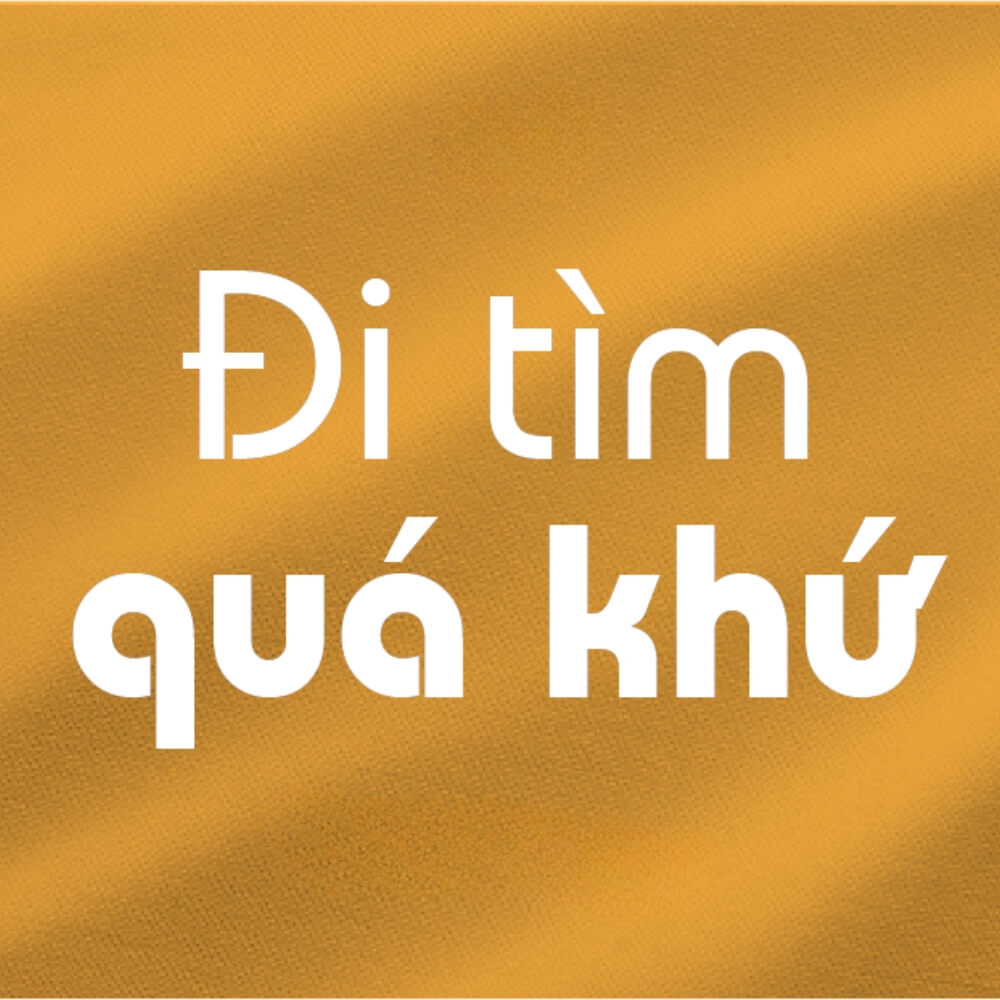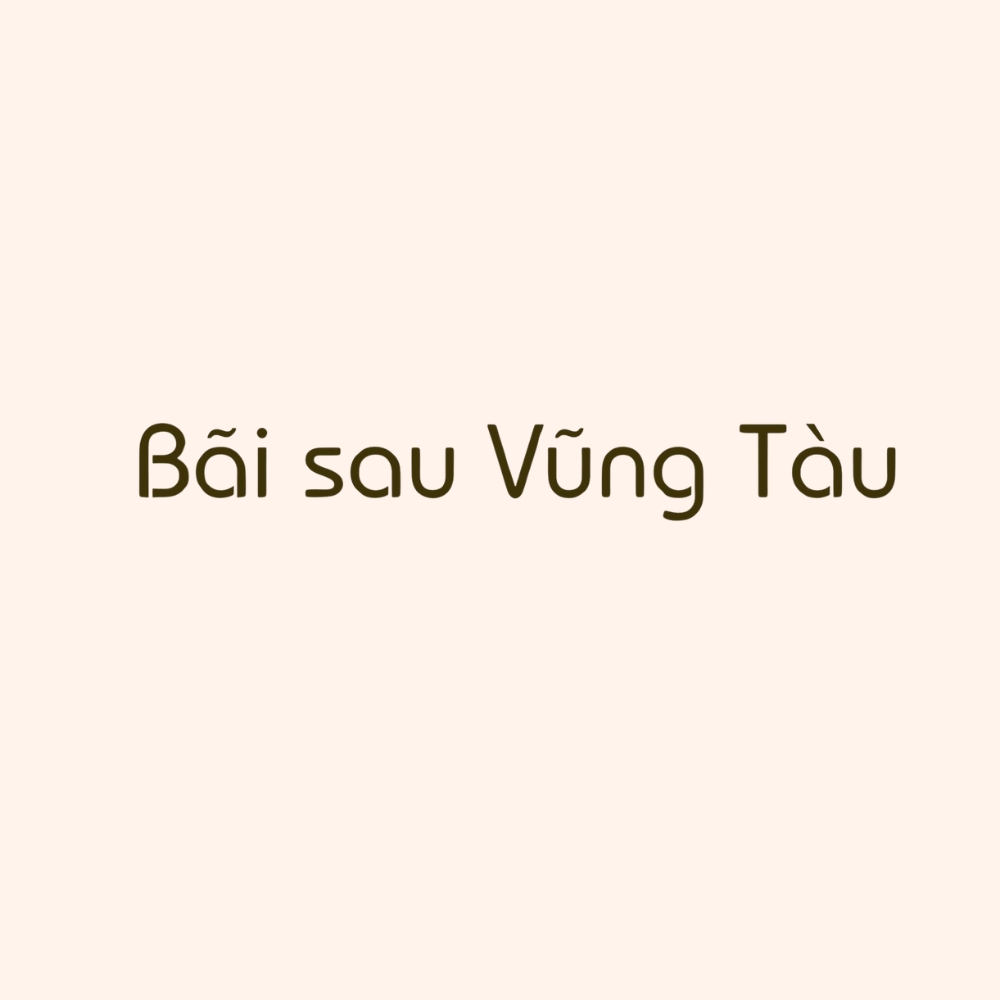
Nhiều designer khi tìm font việt hóa UVN Bai Sau thường gặp tình trạng tải về nhưng chữ hiển thị sai dấu hoặc thiếu ký tự tiếng Việt. Một số file được chia sẻ trên internet chỉ là phiên bản chưa việt hóa hoàn chỉnh nên khi dùng trong poster hoặc thiết kế logo rất dễ phát sinh lỗi. Khi font không chuẩn, bố cục chữ sẽ bị lệch và làm giảm chất lượng thiết kế.
| Tên font | UVN Bãi Sau |
| Kiểu chữ | Sans-serif hiện đại |
| Hỗ trợ | Tiếng Việt đầy đủ |
| Ứng dụng | Logo, poster, banner, tiêu đề |
Bộ font chữ hiện đại uvn bai sau việt hóa thường được sử dụng trong các thiết kế mang phong cách tối giản và hiện đại.
Đặc điểm nổi bật của font việt hóa UVN Bai Sau
Trong nhóm font sans-serif hiện đại, font việt hóa UVN Bai Sau được nhiều designer lựa chọn nhờ cấu trúc chữ gọn gàng và dễ đọc. Font này mang phong cách đơn giản nhưng vẫn đủ cá tính để tạo điểm nhấn trong thiết kế.
Những đặc điểm nổi bật của font này gồm:
- Nét chữ rõ ràng và gọn gàng.
- Phong cách thiết kế hiện đại.
- Dễ đọc ở nhiều kích thước khác nhau.
- Phù hợp với các thiết kế tối giản.
Nhờ những đặc điểm này, download font UVN Bai Sau việt hóa thường được sử dụng trong các dự án thiết kế thương hiệu hoặc truyền thông.
Ứng dụng font việt hoá UVN Bai Sau trong thiết kế
Nhờ kiểu chữ hiện đại và dễ đọc, font việt hóa UVN Bai Sau có thể sử dụng trong nhiều loại thiết kế khác nhau. Font này đặc biệt phù hợp với các dự án cần sự đơn giản nhưng vẫn chuyên nghiệp.
Một số ứng dụng phổ biến của font gồm:
- Thiết kế logo: tạo cảm giác hiện đại và chuyên nghiệp.
- Poster quảng cáo: tiêu đề dễ đọc và rõ ràng.
- Banner truyền thông: phù hợp cho các chiến dịch marketing.
- Thiết kế website: font sans-serif giúp nội dung dễ đọc hơn.
Khi kết hợp với các font serif hoặc script, font uvn bai sang nang viet hoa có thể tạo ra bố cục thiết kế hài hòa và cân đối.
03 lưu ý khi sử dụng font UVN Bai Sau trong thiết kế
Mặc dù font việt hóa UVN Bai Sau khá dễ sử dụng, nhưng designer vẫn nên lưu ý một số điểm để đảm bảo thiết kế đạt hiệu quả tốt nhất.
- Chọn kích thước chữ hợp lý: giúp tiêu đề nổi bật nhưng không quá lớn.
- Kết hợp với font khác: pairing với script hoặc serif giúp bố cục phong phú hơn.
Những lưu ý này sẽ giúp bạn sử dụng font chữ hiện đại UVN Bai Sau việt hóa hiệu quả hơn trong các dự án thiết kế.
Font UVN Bai Sau phù hợp thiết kế gì?
Font này phù hợp cho logo, poster và banner nhờ phong cách chữ hiện đại và dễ đọc.
Font UVN Bai Sau có hỗ trợ tiếng Việt không?
Phiên bản việt hóa hỗ trợ đầy đủ dấu tiếng Việt nên có thể dùng cho thiết kế tại Việt Nam.
Font việt hóa UVN Bai Sau là lựa chọn phù hợp cho những thiết kế mang phong cách hiện đại và tối giản. Khi sử dụng đúng phiên bản download font uvn bai sau việt hóa, designer đảm bảo chữ hiển thị đầy đủ dấu tiếng Việt và giữ được độ chính xác của thiết kế.